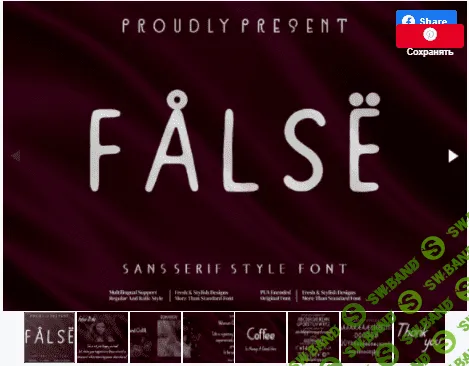
Название: False Note Font (2022)
False Note — красивый шрифт без засечек, подходящий для любых проектов, таких как логотипы, брендинговые проекты, дизайн товаров для дома, упаковка продуктов, кружки, цитаты, плакаты, сумки для покупок, футболки, обложки книг, визитные карточки, пригласительные билеты, поздравительные открытки, этикетки, фотографии, водяные знаки, специальные мероприятия и все другие ваши роскошные проекты, которым нужен первоклассный вкус.